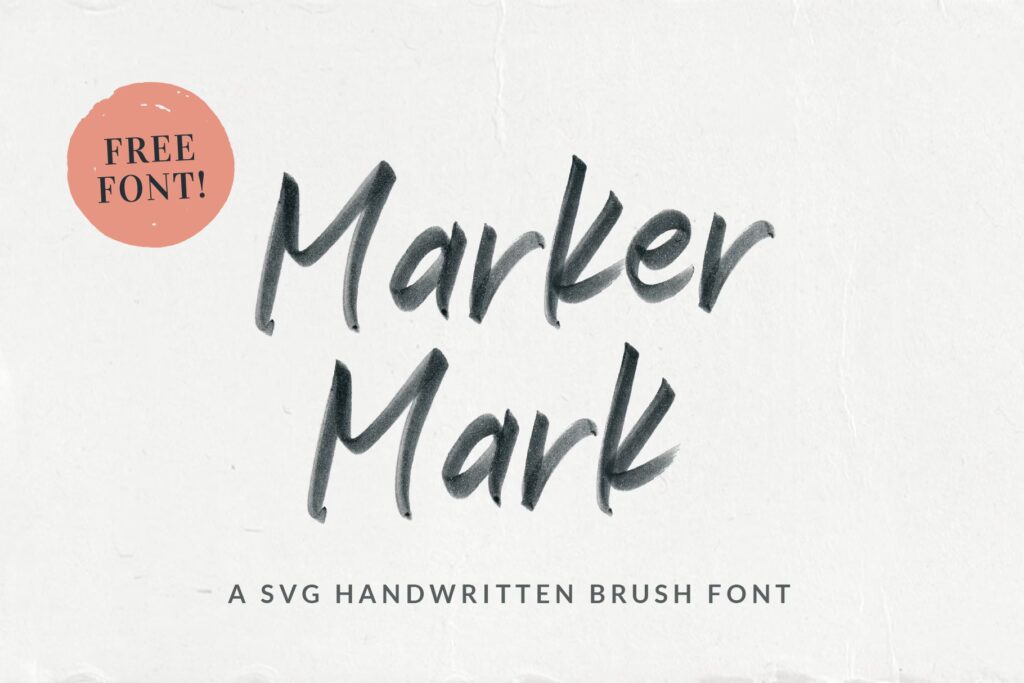
I designverdenen er valget af skrifttype afgørende for at formidle det rette budskab og skabe den ønskede stemning. Mens mange projekter kræver rene og strukturerede skrifttyper, er der situationer, hvor et mere afslappet, kunstnerisk eller personligt udtryk ønskes. Det er her, markør skrifttyper kommer ind i billedet.
Markør skrifttyper efterligner udseendet af tekst skrevet med en markørpen. Dette giver et autentisk, håndlavet look, der kan tilføje en følelse af umiddelbarhed og personlighed til ethvert design. De kan variere enormt i stil – fra brede, dristige streger, der ligner en permanent markør, til finere, mere flydende linjer, der minder om en tuschpen eller endda kalligrafi.
Hvorfor Vælge en Markør Skrifttype?
Brugen af markør skrifttyper er mere end blot en æstetisk præference; det er et værktøj til at formidle specifikke følelser og koncepter. Her er nogle grunde til, at du måske vil overveje at bruge en markør skrifttype i dit næste projekt:
- Autenticitet og Håndlavet Følelse: I en digital tidsalder værdsættes det, der føles ægte og håndlavet. En markør font kan give dine designs et organisk og unikt præg, som standard skrifttyper sjældent kan matche.
- Udtryk for Personlighed: Ligesom håndskrift afslører noget om en persons personlighed, kan en markør font formidle en bestemt vibe – legesyg, dristig, afslappet, kreativ eller endda oprørsk.
- Fang Opmærksomhed: Den ofte uformelle og dynamiske stil af markør skrifttyper kan fange øjet og skabe interesse, især i overskrifter eller korte tekstblokke.
- Alsidinghed: Selvom de har et specifikt look, findes markør skrifttyper i så mange variationer, at de kan bruges i et bredt spektrum af applikationer – fra branding og logoer til invitationer, t-shirts, sociale medie opslag og emballage.
Markør skrifttyper er et kraftfuldt værktøj for designere, der ønsker at bryde med det traditionelle og tilføje et element af kreativitet og spontanitet.
Forskellige Stilarter af Markør Skrifttyper
Markør skrifttyper er ikke en ensartet kategori. De spænder over et bredt spektrum af stilarter, der afspejler forskellige typer markører og skrivemåder. At forstå disse variationer hjælper dig med at vælge den rette font til dit specifikke formål.
- Den Permanente Markør Stil: Disse fonde efterligner ofte de brede, dristige streger fra en tyk permanent markør. De er ideelle til overskrifter, plakater og elementer, der skal have stor visuel gennemslagskraft. De kan have et lidt råt eller uperfekt look, der bidrager til deres autenticitet.
- Den Flydende Tusch/Felt-Tip Stil: Disse fonde har finere, mere flydende streger og kan ligne tekst skrevet med en tyndere tuschpen. De er ofte mere læselige i mindre størrelser og kan bruges til mere detaljerede designs, invitationer eller endda kortere tekstblokke.
- Kalligrafisk Markør: Nogle markør fonde kombinerer markør-looket med elementer af kalligrafi, hvilket resulterer i elegante, men stadig håndskrevne stilarter. Disse er populære til bryllupsinvitationer, mode-relateret design eller personlige mærker.
- Street Art/Graffiti Inspireret: Disse fonde fanger energien og stilen fra street art og graffiti. De er ofte dynamiske, kantede og kan have et oprørsk eller urbant præg. Perfekt til branding, t-shirts og designs, der skal udstråle en rå og udtryksfuld attitude.
- Børnevenlige/Legesyge: Nogle markør fonde har en mere afrundet, legesyg eller endda crayon-lignende stil, der er ideel til designs rettet mod børn eller projekter, der skal føles muntre og uformelle.
Udvalgte Markør Skrifttyper og Deres Anvendelser
Her er en gennemgang af nogle typer af markør skrifttyper og hvor de kan bruges, baseret på de stilarter, der ofte findes:
Til Dristige Overskrifter og Branding:
Fonter med tykke, dristige streger, der ligner permanent markør, er fremragende til at skabe opmærksomhed. De er velegnede til:
- Plakater og flyers
- Logoer og brandidentitet (især for afslappede eller kreative mærker)
- Titler på bogomslag eller albums
- Sociale medie grafik, der skal skille sig ud
Denne stil kan give et robust og selvsikkert udtryk. Tænk på fonde som dem beskrevet som 'Marker Attack' eller 'Blackout', som er designet til at være iøjnefaldende og kraftfulde.
Til Personlige Invitationer og Mode:
Mere flydende og elegante markør fonde, ofte med en feminin eller kalligrafisk kant, er perfekte til at tilføje et personligt og sofistikeret touch. Anvendelser inkluderer:
- Bryllups- og festinvitationer
- Hilsenskort
- Mode- og skønhedsrelateret branding
- Citater og tryk på tøj
Disse fonde (som f.eks. 'Pearly Smiles' eller den 'feminine marker font' nævnt i kildeteksten) udstråler ofte ynde og en håndskrevet charme, der føles intim og eksklusiv.
Til Urban og Kantet Design:
Markør fonde inspireret af street art og graffiti har en dynamisk og rå energi. De er ideelle til:
- T-shirt designs
- Musikrelateret grafik (albumcovers, koncertplakater)
- Branding for urbane mærker
- Design, der skal føles oprørsk eller alternativt
Fonter som 'SlickStick' eller 'Rebel Marker' fanger denne æstetik med deres ufiltrerede streger og kantede former, der minder om tags og murmalerier.
Til Afslappede og Legesyge Projekter:
Blødere, mere afrundede eller uformelle markør fonde er fantastiske til at skabe en venlig og tilgængelig følelse. De passer godt til:
- Designs rettet mod børn (bøger, legetøjspakker)
- Sociale medie opslag med et afslappet budskab
- Håndværks- og hobbyrelateret branding
- Enhver situation, der kræver et muntert og ukompliceret udtryk
Disse fonde (som f.eks. den 'crayon-inspired' font eller 'Hakuro') har ofte et naivt eller charmerende look, der appellerer bredt.
Til Professionelle, Men Unikke Projekter:
Nogle markør fonde formår at kombinere det håndlavede look med en vis grad af renhed og læselighed, hvilket gør dem egnede til mere professionelle anvendelser, hvor et personligt touch stadig ønskes.
- Visitkort og brevpapir
- Signatur-logoer
- Præsentationstitler
- Hjemmeside-headers
Fonter beskrevet som 'clean and minimal' eller 'signature designs' (som f.eks. 'Deustchen' eller den 'felt tips' inspirerede font) kan give et unikt, men stadig poleret udseende.
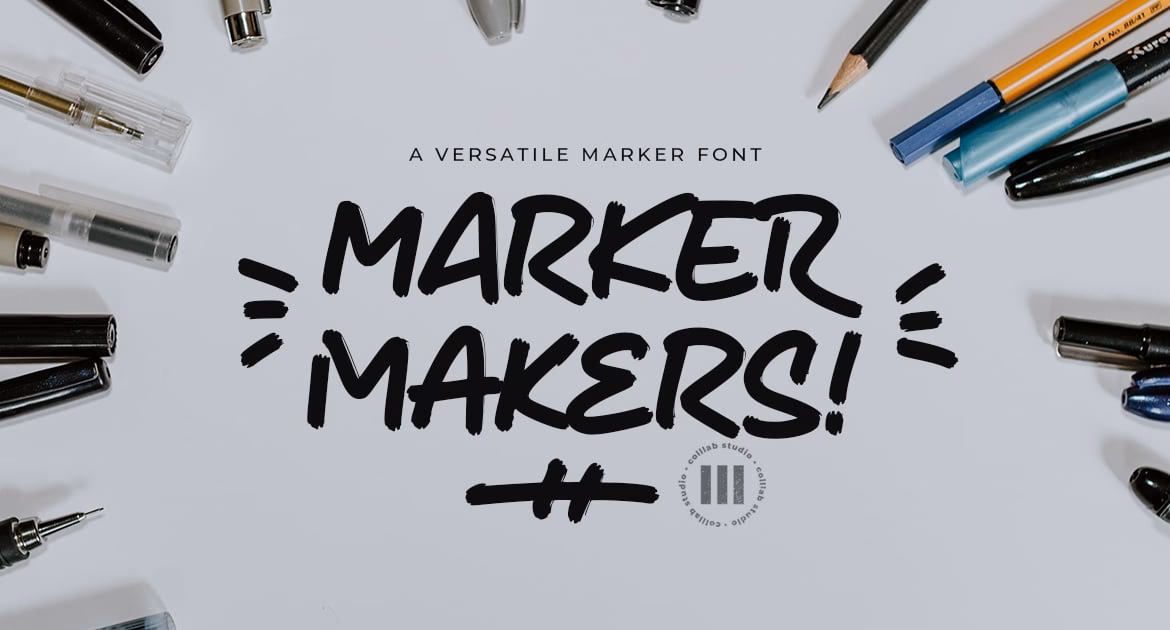
Sammenligning af Markør Stilarter
| Stilart | Karakteristik | Typiske Anvendelser | Stemning |
|---|---|---|---|
| Fed Markør | Brede, dristige streger; ofte uperfekt kant | Overskrifter, plakater, dristig branding | Kraftfuld, Utvetydig, Rå |
| Flydende/Tusch | Finere, mere flydende linjer; ofte mere ensartet | Invitationer, kort, detaljeret tekst | Elegant, Let, Håndskrevet charme |
| Street Art | Dynamiske, kantede former; kan ligne graffiti | Urban branding, tøjtryk, musik grafik | Oprørsk, Energisk, Rå |
| Legesyg/Børnevenlig | Afrundede former; kan ligne crayon | Børnedesign, afslappede opslag | Munter, Uskyldig, Tilgængelig |
| Kalligrafisk | Flydende, forbundne bogstaver; elegant flair | Bryllup, mode, personlig branding | Sofistikeret, Romantisk, Unik |
Ofte Stillede Spørgsmål om Markør Skrifttyper
Når man overvejer at bruge markør skrifttyper, dukker der ofte spørgsmål op. Her er svar på nogle af de mest almindelige:
Er markør skrifttyper svære at læse?
Dette afhænger meget af den specifikke font og hvordan den bruges. Meget dristige, rodede eller dynamiske markør fonde er bedst egnet til overskrifter eller korte sætninger, hvor læselighed på afstand er vigtig. Finere eller mere ensartede markør fonde kan være læselige i mindre størrelser, men de fleste markør fonde er generelt ikke ideelle til lange tekstblokke som brødtekst i en bog eller en artikel. De fungerer bedst som et visuelt element, der supplerer anden, mere læselig tekst.
Hvor finder jeg markør skrifttyper?
Der findes et væld af steder online, hvor du kan finde markør skrifttyper. Mange font-markedspladser (både gratis og betalte) tilbyder kategorier eller tags for 'marker' eller 'handwritten' fonde. Nogle designblogs og hjemmesider samler lister over populære markør fonde. Det er vigtigt at tjekke licensen for hver font, især hvis du planlægger at bruge den til kommercielle projekter.
Findes der gratis markør skrifttyper?
Ja, der findes mange gratis markør skrifttyper tilgængelige online. Dog er gratis fonde ofte kun licenseret til personlig brug. Hvis du har brug for en font til et kommercielt projekt (f.eks. et logo for en virksomhed, et design til salg), skal du sikre dig, at licensen tillader kommerciel brug, eller overveje at købe en kommerciel licens for en premium font.
Hvilke filformater bruger markør skrifttyper?
Markør skrifttyper, ligesom de fleste moderne skrifttyper, kommer typisk i formater som OTF (OpenType Font), TTF (TrueType Font) og WOFF/WOFF2 (Web Open Font Format). OTF og TTF er standard for desktop-brug i designsoftware, mens WOFF-formater er optimeret til brug på hjemmesider.
Kan jeg bruge markør skrifttyper i ethvert designprogram?
Ja, så længe dit designprogram (f.eks. Adobe Photoshop, Illustrator, InDesign, Figma, Canva, Microsoft Word, etc.) understøtter installation og brug af OTF eller TTF skrifttyper, kan du bruge de fleste markør fonde. Nogle fonde har avancerede funktioner (som ligaturer eller alternative tegn), der kræver OpenType-understøttelse i softwaren for at blive fuldt udnyttet.
Hvordan styler jeg bedst markør tekst?
For at forstærke det autentiske markør-look kan du overveje at tilføje teksturer, der efterligner papir eller filt, eller give teksten en let uregelmæssig kant eller skygge for at simulere dybde og et håndtegnet udseende. At bruge store bogstaver eller en kombination af store og små bogstaver kan også ændre fontens udtryk markant.
Markør skrifttyper er et spændende valg for designere, der ønsker at bryde med det traditionelle og tilføje et lag af autenticitet, alsidighed og personlig flair til deres projekter. Ved at udforske de mange forskellige stilarter kan du finde den perfekte markør font til at gøre dit næste design uforglemmeligt.